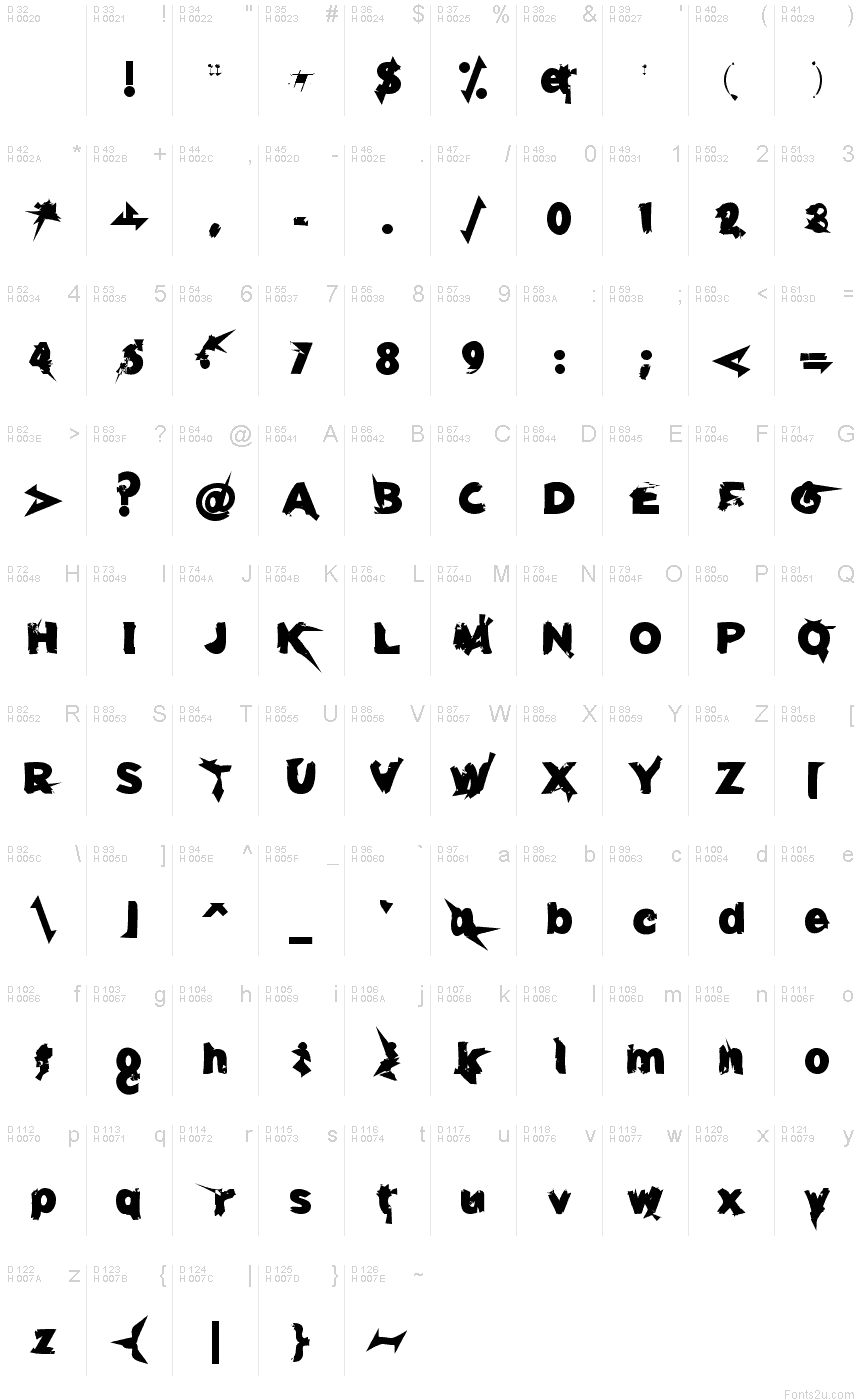
u27fog
خط U27fog من تصميم Gaston Yagmourian هو خط عرض مجاني ومشوّه، يتميز بصورة ظلية خشنة ومقطعة. تبدو الحروف كأشكال ثقيلة تعرضت للتقطيع والتشظي والإزاحة، حيث تمزج بين الحجم الناعم والشظايا الحادة، مما يجعل الخط بأكمله يبدو كأنه مطبوع على ملصق ممزق أو نتاج تصادم رقمي خشن.
إنه مناسب تماماً لنشرات النوادي، والملصقات التجريبية، وأغلفة الألبومات، وعناوين المجلات، والبطاقات التعريفية التي يمكن فيها للكلمات القصيرة أن تحمل هذا الوزن المتكسر؛ وبما أنه خط مجاني، فهو مفيد أيضاً لنماذج العلامات التجارية السريعة أو رسومات الفعاليات لمرة واحدة. استخدمه عندما تريد أن يكون الخط نفسه بمثابة صورة، مع كتلة كافية للحفاظ على تماسك الكلمة حتى مع تكسر حوافها.